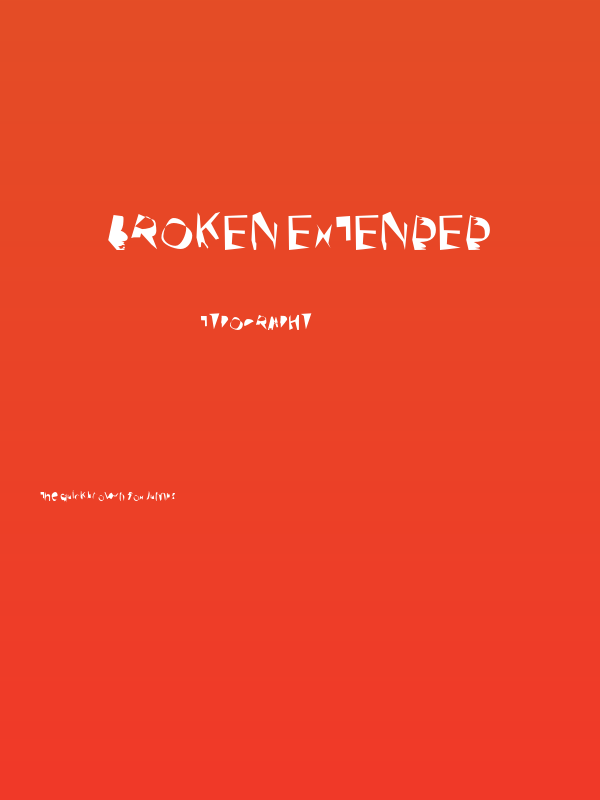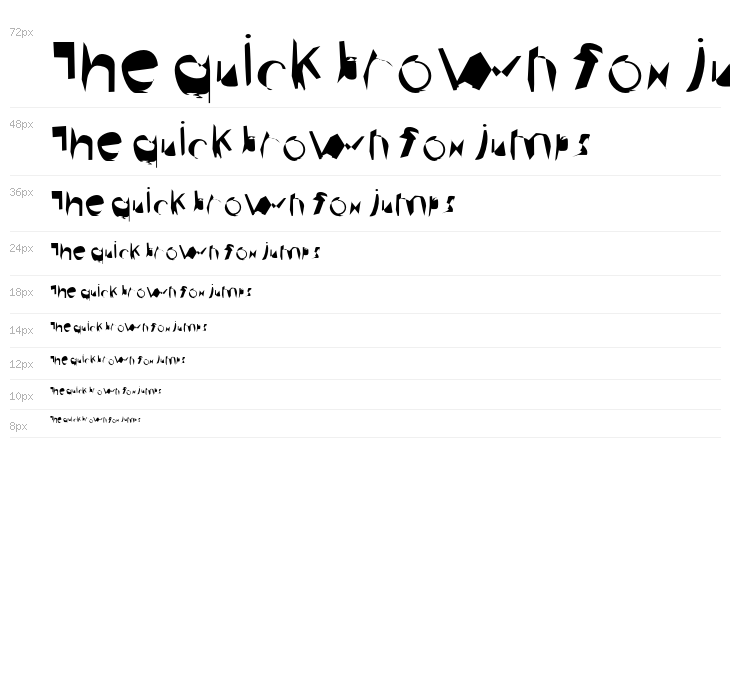
Broken Extended Font
✎ Distorted Eroded
| Stile generale | Modern, Edgy |
| Progetti proposti | Ideal for album covers, edgy posters, modern art projects, and any design requiring a bold, unconventional look. |